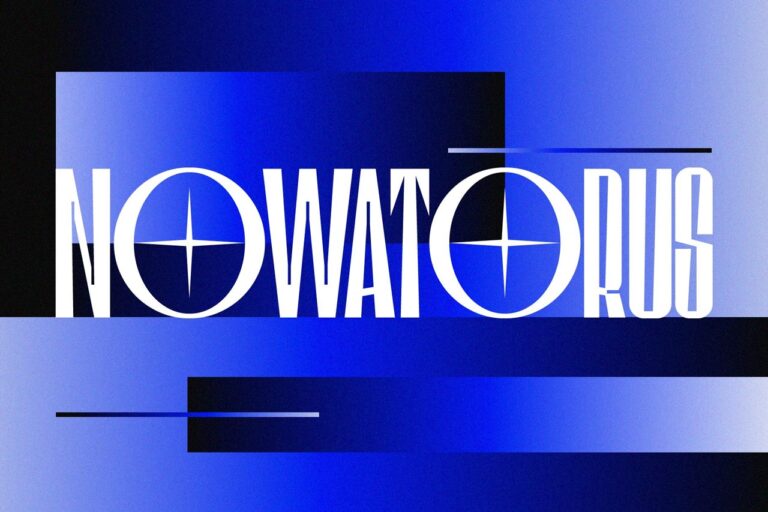
SK Nowatorus là một kiểu font với các nét độc đáo.
Kiểu chữ này thách thức những ý tưởng thông thường về cấu trúc ký hiệu và sự hài hòa trong đường nét sắp chữ. Các ký hiệu kiểu chữ dựa trên độ tương phản trung bình của độ dày và độ tương phản của hình dạng của chính các ký hiệu đó. Phông chữ kết hợp cả các ký tự hẹp của bộ chính và các ký tự bổ sung ở kích thước rộng. Điều này, cùng với một loạt các lựa chọn thay thế và chữ ghép, mang lại cơ hội lớn cho các thử nghiệm sáng tạo.
SK Nowatorus hỗ trợ đa ngôn ngữ Latin Pro và Cyrillic Pro. Kiểu chữ này hoàn hảo cho thiết kế áp phích và cho một tập hợp các khối văn bản nhỏ do sự hiện diện của bộ chữ in hoa và chữ thường.